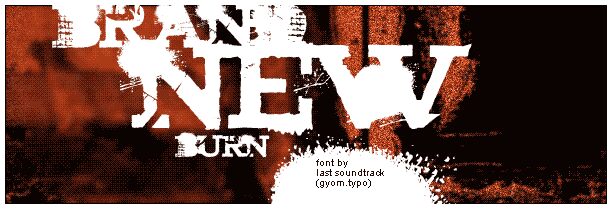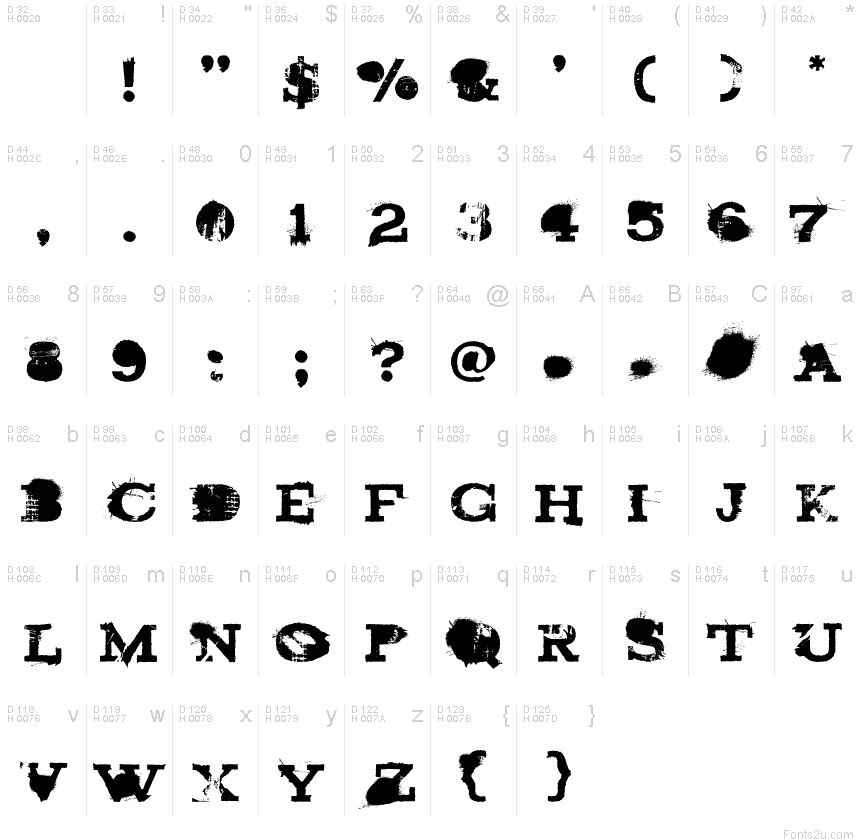
Brand New Burn autorstwa Gyomsegs to darmowy, erodowany krój typu display, zbudowany z ciężkich, ściśle spakowanych wielkich liter. Szorstkie krawędzie, wyskrobane szczeliny i smugowate wnętrza nadają szerokim formom liter wygląd farby startej ze starego plakatu ulicznego.
Potrafi zmienić nagłówek w część dzieła sztuki zamiast neutralnego tekstu. Zniszczona faktura druku jest szczególnie przekonująca w przypadku gadżetów punkowych i plakatów muzycznych, a kolejne zastosowania znajdzie w grafikach deskorolkowych i stylizowanych opakowaniach.